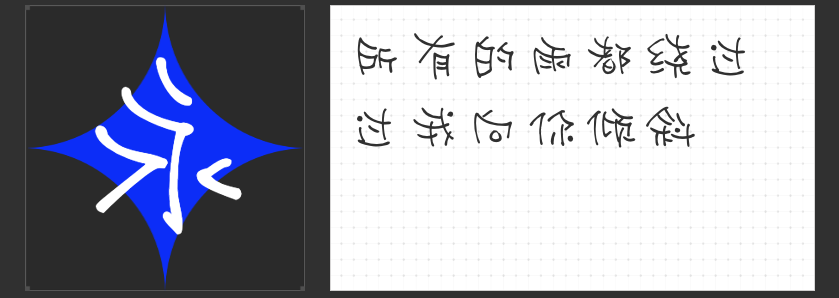
清新文艺“小豆岛”,让文字也充满情感
在数字化时代,字体不仅仅是信息的载体,更是情感和风格的传递者。今天,我要为大家推荐四款来自小豆岛系列的清新文艺手写字体,它们各具特色,无论是用于设计还是排版,都能让你的作品或文字瞬间充满温度和故事感。
1.小豆岛默陌秀丽简
纵情释放你的文艺气息吧!这款字体笔锋有力,每一笔一划都透露着传统书法的写意风格。点划看似随意,实则疏密有致,通过巧妙的节奏塑造出线条的粗细变化和节点,让文字仿佛拥有了生命,跃然纸上。
2.小豆岛默陌乐童简
童心是比野心更难得的梦想。这款字体以其上松下紧的儿童字结构,搭配简单稚拙的笔画,宽细一致,让人一眼就能感受到孩童纯真无邪的书写特点。无论是用于儿童读物、教育材料还是创意设计中,都能轻松营造出温馨、欢快的氛围。
这款字体以其整体倾斜的结构,打破了传统书法的规矩,通过正统笔画间架的解构,创造出一种重心倾斜的视觉感,充满了活泼谐趣的气息。它非常适合用于二次元、旅行、鬼畜等视频场景,为作品增添一抹独特的趣味和动感。
治愈一切不开心。这款字体字形丰腴圆润,仿佛是用轻松自由的水墨笔触书写而成。笔画节点随性而不拘小节,给人一种温暖而治愈的感觉。它的应用性强,可以随意拉伸使用,无论是海报设计、社交媒体还是日常笔记,都能让你的文字散发出独特的魅力。
小豆岛系列手写字体,每一款都承载着不同的情感和风格,它们不仅让文字更加美观,更让文字成为了表达个性和情感的艺术品。快来选择一款你喜欢的字体,让文字也充满情感吧!